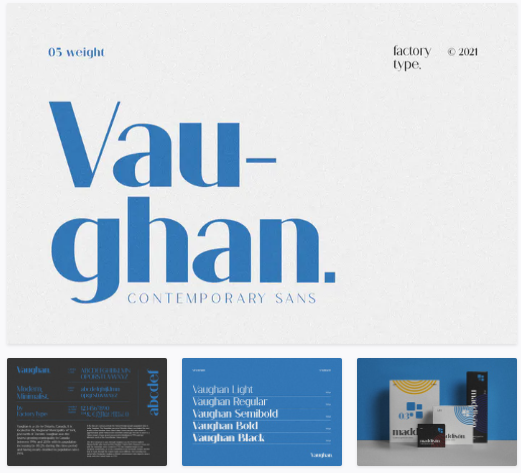
Vaughan - это современный и минималистичный шрифт с засечками.
Различные веса предлагают множество вариантов, чтобы помочь вам найти лучший типографский цвет для вашего проекта.
Это непревзойденный sans serif для разнообразия ваших заголовков, визуальной идентификации брендинга, плакатов, логотипов, журналов и так далее.